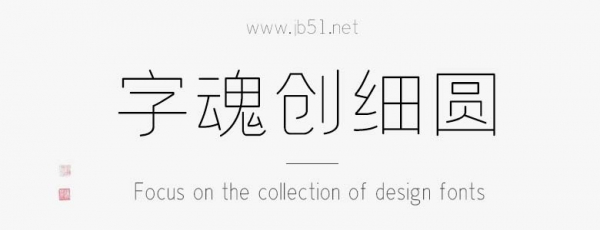
字魂創(chuàng)細(xì)圓字體是由字魂字庫推出的黑體字體,該字體包含6763個(gè)中文、字母、 符號(hào)和數(shù)字,具有簡約的風(fēng)格,具有中國風(fēng)的風(fēng)格,適合應(yīng)用于藝術(shù)設(shè)計(jì)、平面宣傳設(shè)計(jì)、網(wǎng)頁設(shè)計(jì),書法字帖等領(lǐng)域。
字魂創(chuàng)細(xì)圓字體是一款商用的圓體字體,該字體包含6763個(gè)中文、字母、 符號(hào)和數(shù)字,具有簡約的風(fēng)格,可以滿足您設(shè)計(jì)上的各種需求,該字體主要用于黨政公務(wù)等場景, 您不但可以在字魂網(wǎng)下載字魂創(chuàng)細(xì)圓字體,同時(shí)還有眾多毛筆書法字體、創(chuàng)意字體等可供選擇!